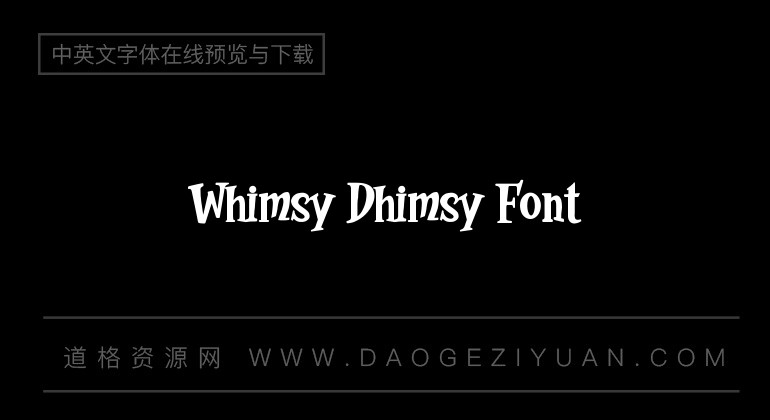
Whimsy Dhimsy Font
Whimsy Dhimsy是一种手写风格的字体,具有一种轻快、活泼和有趣的感觉。它的设计灵感来自于手写字母,每个字母都有一种独特的形状和流畅的线条。 这种字体的特点是大小写字母都具有装饰性和可读性,适用于各种不同的项目,如儿童书籍、漫画、宣传册和广告等等。此外,它还包含了大量的符号和标点符号,使得在设计中可以更加灵活。 Whimsy Dhimsy是一种自然、轻松、有趣的字体,可以为你的设计注入一份乐趣和活力。
Whimsy Dhimsy Font是一款非常不错的手写艺术字体,具有很好的视觉感,适合于文化类的宣传设计、商业类品牌的广告和产品包装设计以及个性化文字排版等较多场景。